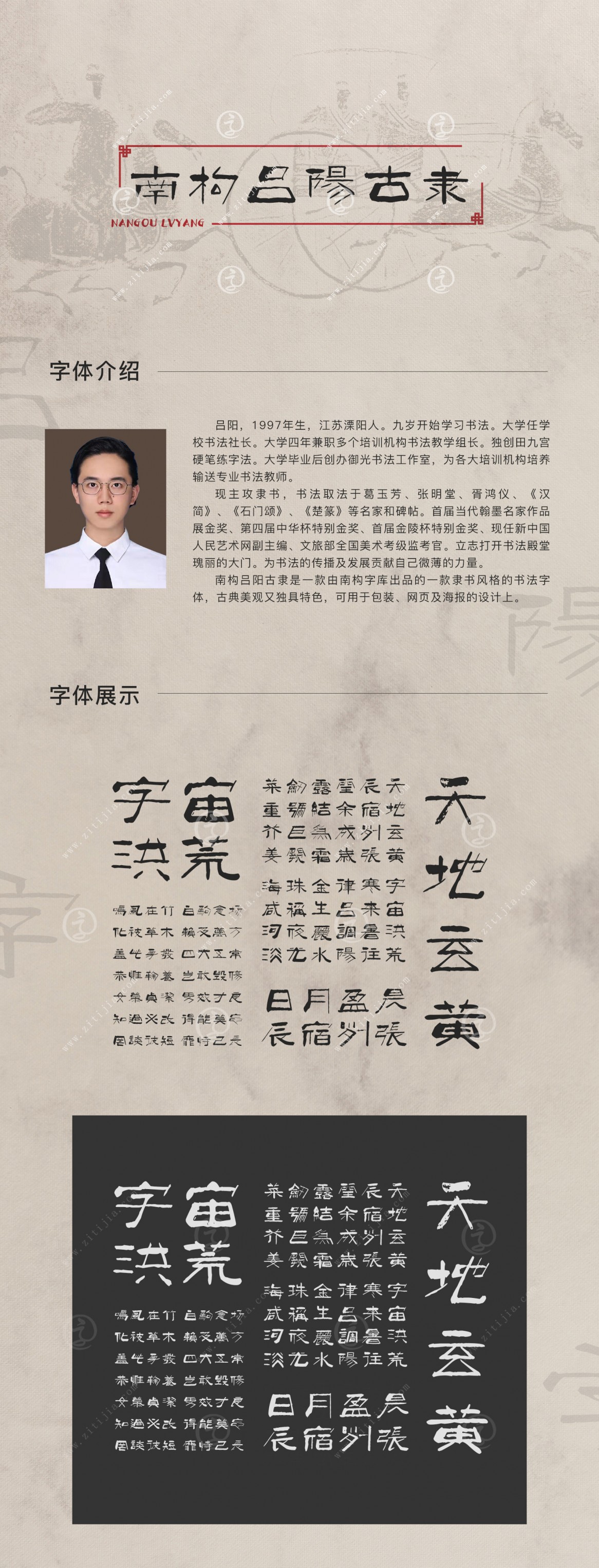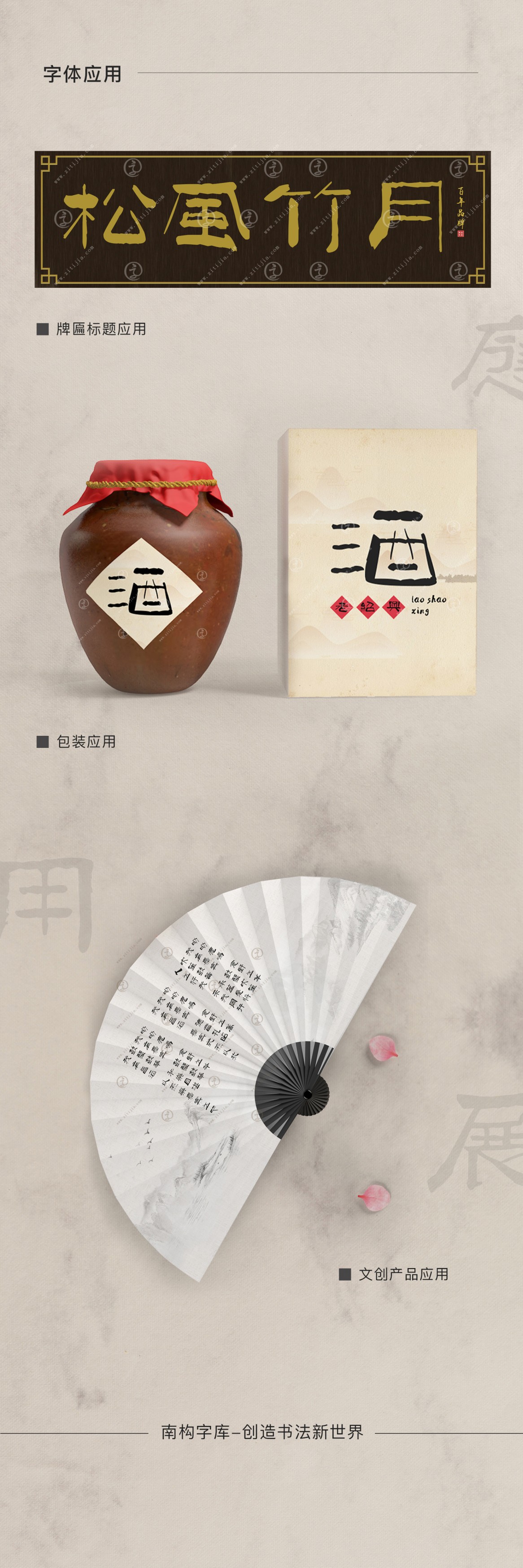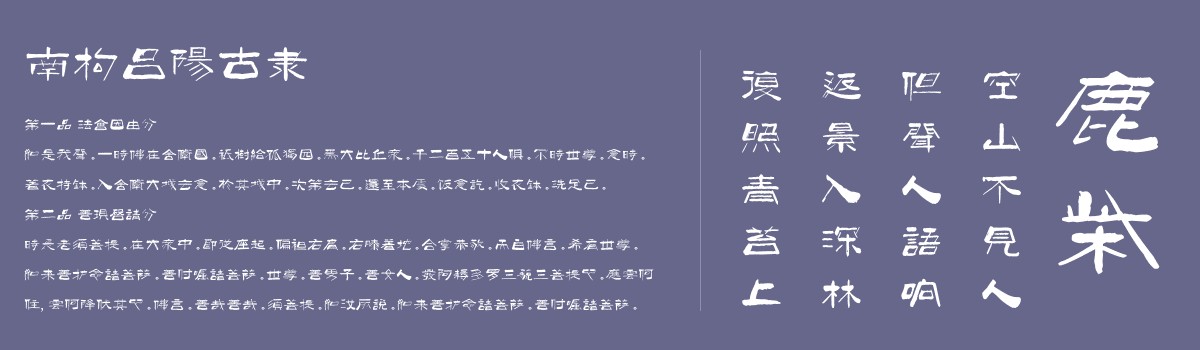
南构吕阳古隶
南构吕阳古隶是一款由南构字库出品的一款隶书风格的书法字体,古典美观又独具特色,可用于包装、网页及海报的设计上。
作者简介:吕阳,1997年生,江苏溧阳人。九岁开始学习书法。大学任学校书法社长。大学四年兼职多个培训机构书法教学组长。独创田九宫硬笔练字法。大学毕业后创办御光书法工作室,为各大培训机构培养输送专业书法教师。